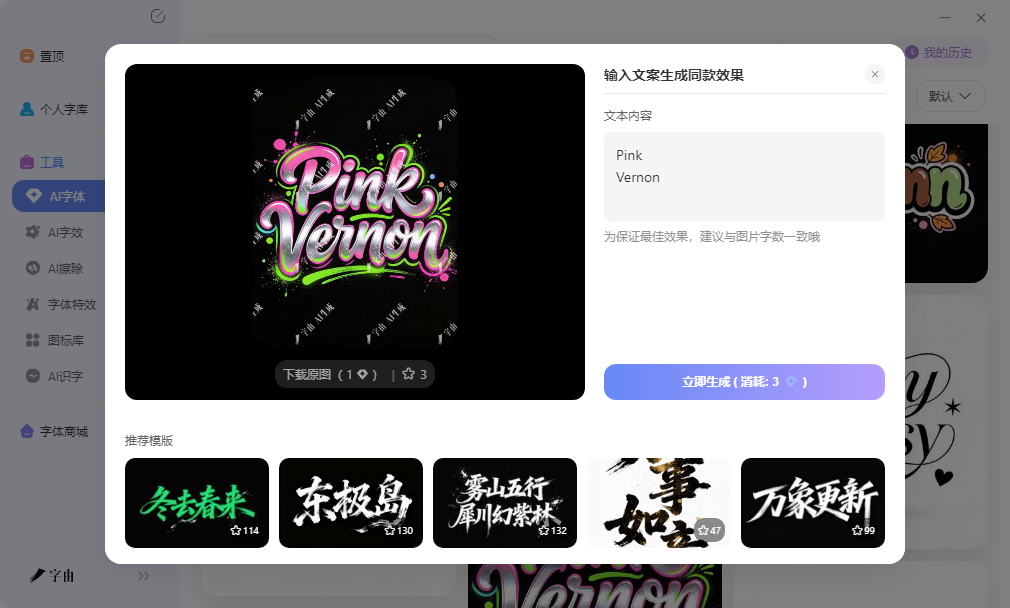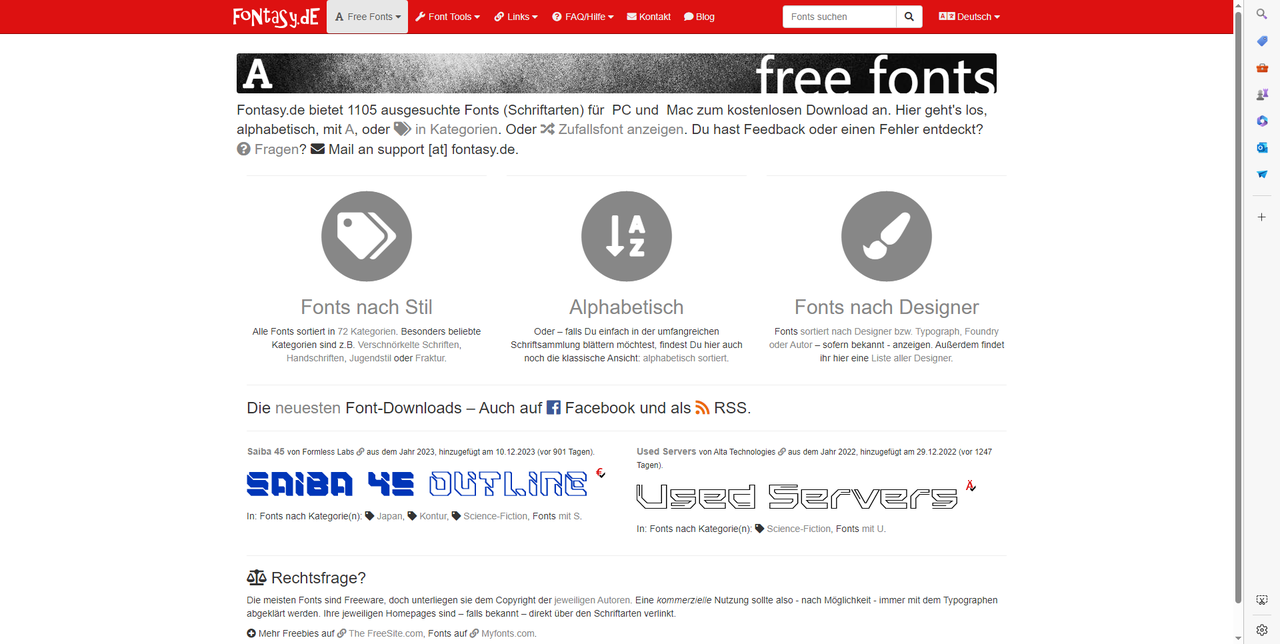
英文手写字体下载,签名和品牌标语轻松做
做品牌标语或者个人签名,黑体和宋体总显得太正式。手写字体带一点自然的不规则感,像是有人亲手写上去的,客户看了会觉得更有亲和力。英文手写体尤其如此,流畅的连笔和自然的起落笔,能让品牌气质从"工业化"变成"有温度"。找英文手写字体的渠道时,不光要看字形好不好看,还要看授权是否允许商用,以及字符集是否完整。这篇文章分享的五个平台,从中文管理到海外手写库都有覆盖。
字由的字体库里,英文手写体并不是一个独立的分类,而是分散在不同中文字体的西文配套部分里。找这类手写体时,可以先点进手写体分类,再勾选免费商用标签。预览框里输入一段英文文案,比如品牌Slogan或者签名内容,观察连笔是否自然、字距是否舒适。有些手写体的西文部分在小字号时连笔会糊在一起,放大后才发现笔画纠缠不清;有些则在大字号时显得过于松散,缺乏凝聚力。字由的预览支持调整字号,从12pt到72pt都能看到效果。
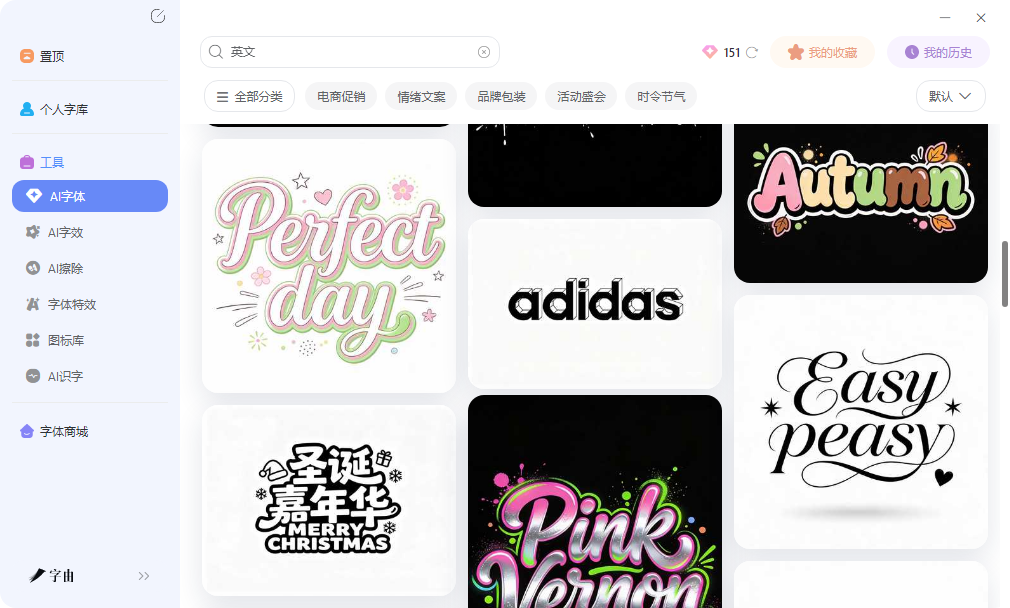
AI字体功能对英文手写体需求也有帮助。模板库里有不少模拟手写质感的特效模板,比如把文字做成毛笔飞白效果、水彩晕染效果、马克笔涂鸦效果等。选一个手写风格的模板,输入英文文案,生成一张透明背景的PNG图片,可以直接放进品牌手册或者电商详情页里。这种方式比找手写体再自己调效果要快不少,尤其适合时间紧、需要快速出方案的情况。生成的图片分辨率足够应付屏幕显示和一般印刷需求。
2、Fontasy
Fontasy的分类体系比较细致,导航按Sans Serif、Serif、Script、Display等做了划分,手写体主要集中在Script分类下。每款字体都配有预览图和下载按钮,部分还展示了设计师信息和创作背景。
作为英文手写字体的渠道,Fontasy的优势在于分类清晰、浏览体验顺畅。Script分类之外,Handwritten分类下也有不少带手写气质的资源,可以搭配浏览。网站上的字体很多标注了免费下载,授权方面大部分允许个人使用,商用前建议确认条款。预览功能支持输入自己的英文文案查看效果,字号可调。对于需要按精确分类逐步筛选、不喜欢在海量结果里翻找的用户来说,这里的导航效率比较高。定期来逛能看到新上架的字体,保持手写体储备的更新。
3、Fonts2u
Fonts2u是一个大型免费字体站,手写体资源量比较大。网站支持按风格、语言等维度筛选,找特定方向的英文手写体时效率较高。预览框支持输入自己的英文文案查看效果,方便判断在实际排版中的表现。
作为英文手写字体的来源,Fonts2u的优势在于资源量大、浏览顺畅。网站上很多手写体标注了免费下载,但授权类型不完全统一,有些仅限个人使用,下载前建议查看详情页确认。分类体系比较直观,可以按热度排序,快速找到下载量高的热门手写体,这种排序方式对不确定选什么、想跟随大众选择的用户比较友好。对于喜欢在大量选项里慢慢淘、找到最契合项目气质那款字体的用户来说,这里的体量比较够用。手写体之外,Brush和Calligraphy分类下也有不少相关资源,可以搭配浏览扩大选择范围。
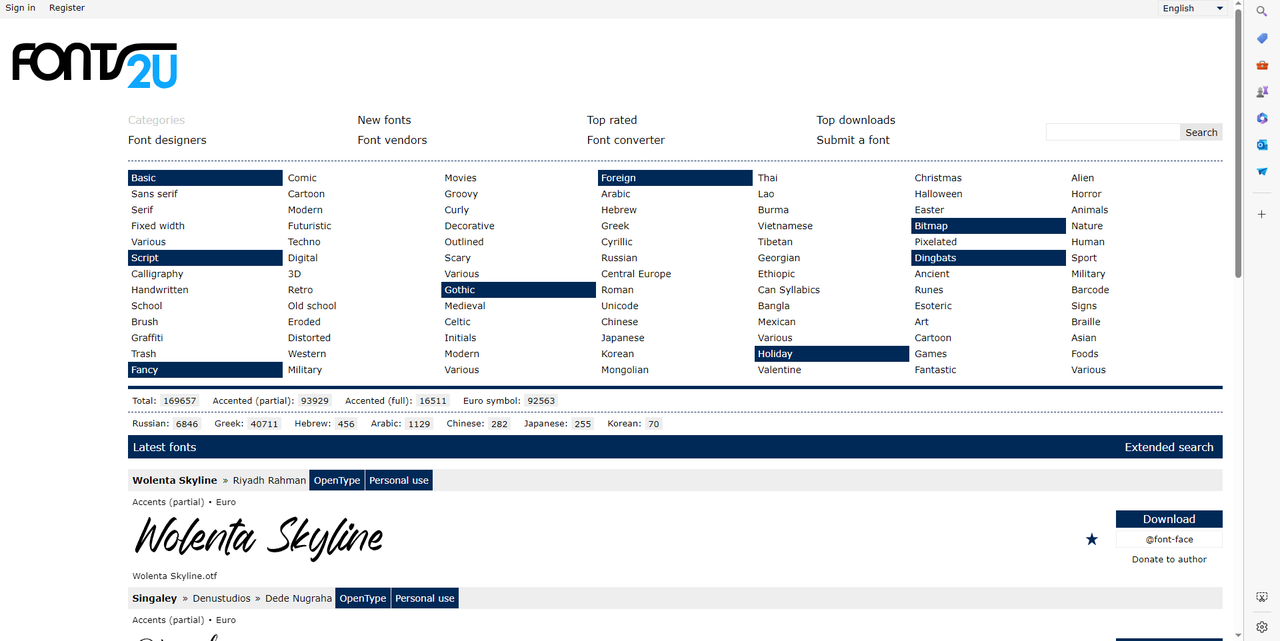
4、Free-Fonts
Free-Fonts的Signiture Fonts分类专门收录签名字体,目前有一百多款资源。这些字体偏向个人标识用途,笔画流畅、连笔自然,适合做品牌创始人签名、产品手写标签或者婚礼请柬署名。
作为英文手写字体的渠道,它的优势在于分类明确,找签名用途的字体时路径清晰。每款字体都配有预览图和下载按钮,部分还展示了实际签名效果,比如用该字体写出来的名字在名片上的呈现效果。授权信息在详情页有标注,下载前可以确认是否允许商用。对于需要快速找到一批签名字体、批量对比后确定最终方案的用户来说,这里的分类效率比较高。下载流程顺畅,获取的字体文件为标准格式,安装后在设计软件里直接调用。
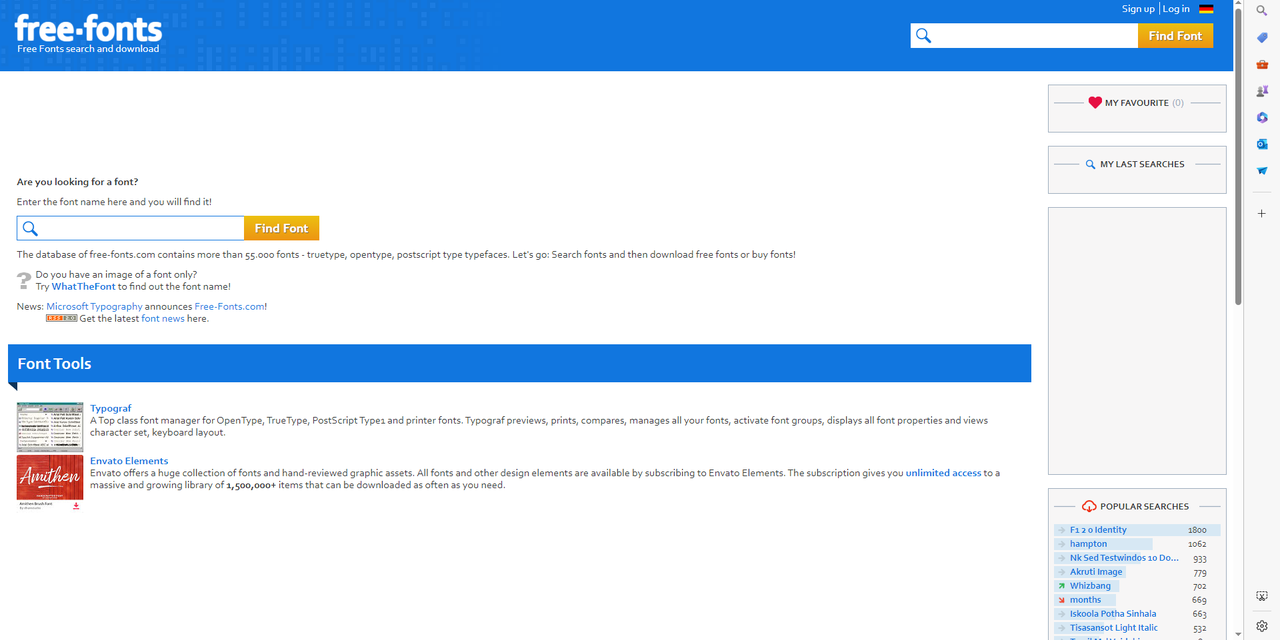
5、FontFreak
FontFreak是一个老牌字体下载站,手写体分类下收录了大量资源。每款字体都有清晰的展示图,部分还展示了设计师的创作过程。分类体系比较细致,可以按风格标签逐步筛选,从优雅连笔到粗犷涂鸦都有覆盖。
作为英文手写字体的来源,FontFreak的优势在于资源量大、更新频繁。很多字体来自独立设计师,风格比较个性化,在主流渠道不太容易找到。预览功能支持输入自己的英文文案查看效果,方便判断在实际排版中的表现。下载前建议仔细查看授权说明,确认商用条款后再使用。字体文件为标准TTF或OTF格式,安装后在设计软件里直接调用,兼容性没有问题。对于需要大量手写体储备、喜欢探索不同书写气质的设计师来说,这里的更新频率和资源广度比较够用。
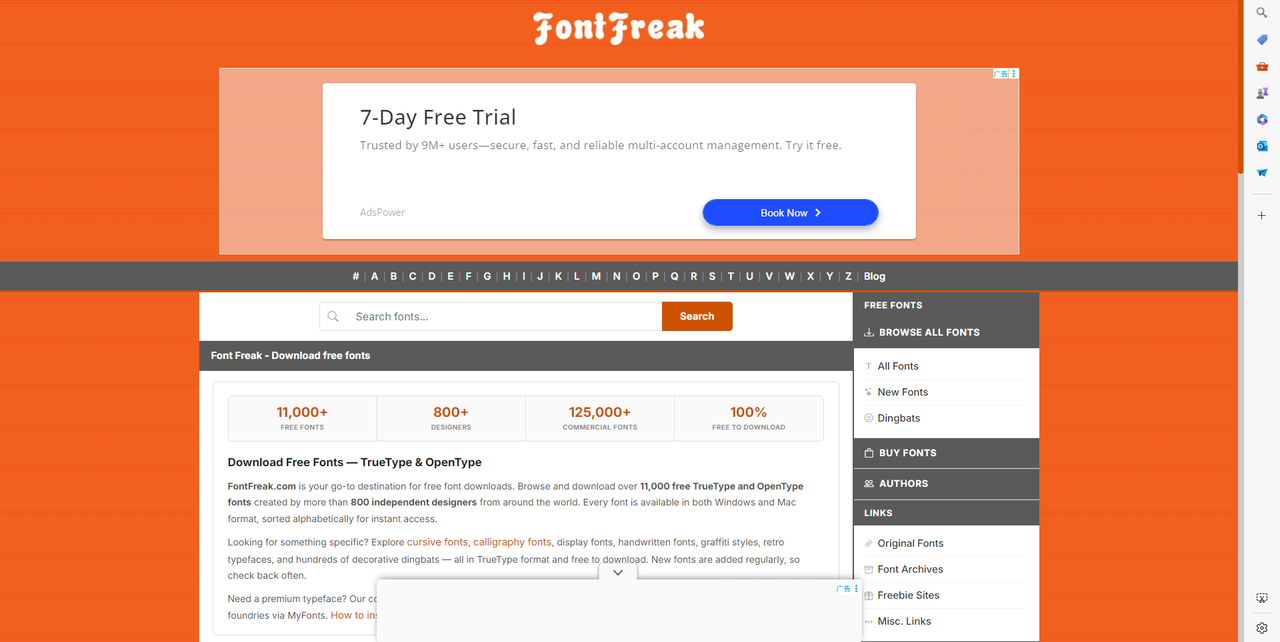
如果说想要一个带手写感的品牌标语或者签名,字由的中文手写体配套西文在混排一致性方面表现不错,配合AI字体的手写质感特效非常好用。FontFreak的独立设计师资源有个性。Free-Fonts的签名字体分类明确,找签名用途时效率高。Fonts2u资源量大,适合批量探索。Fontasy分类清晰,按Script和Handwritten浏览路径比较直观。